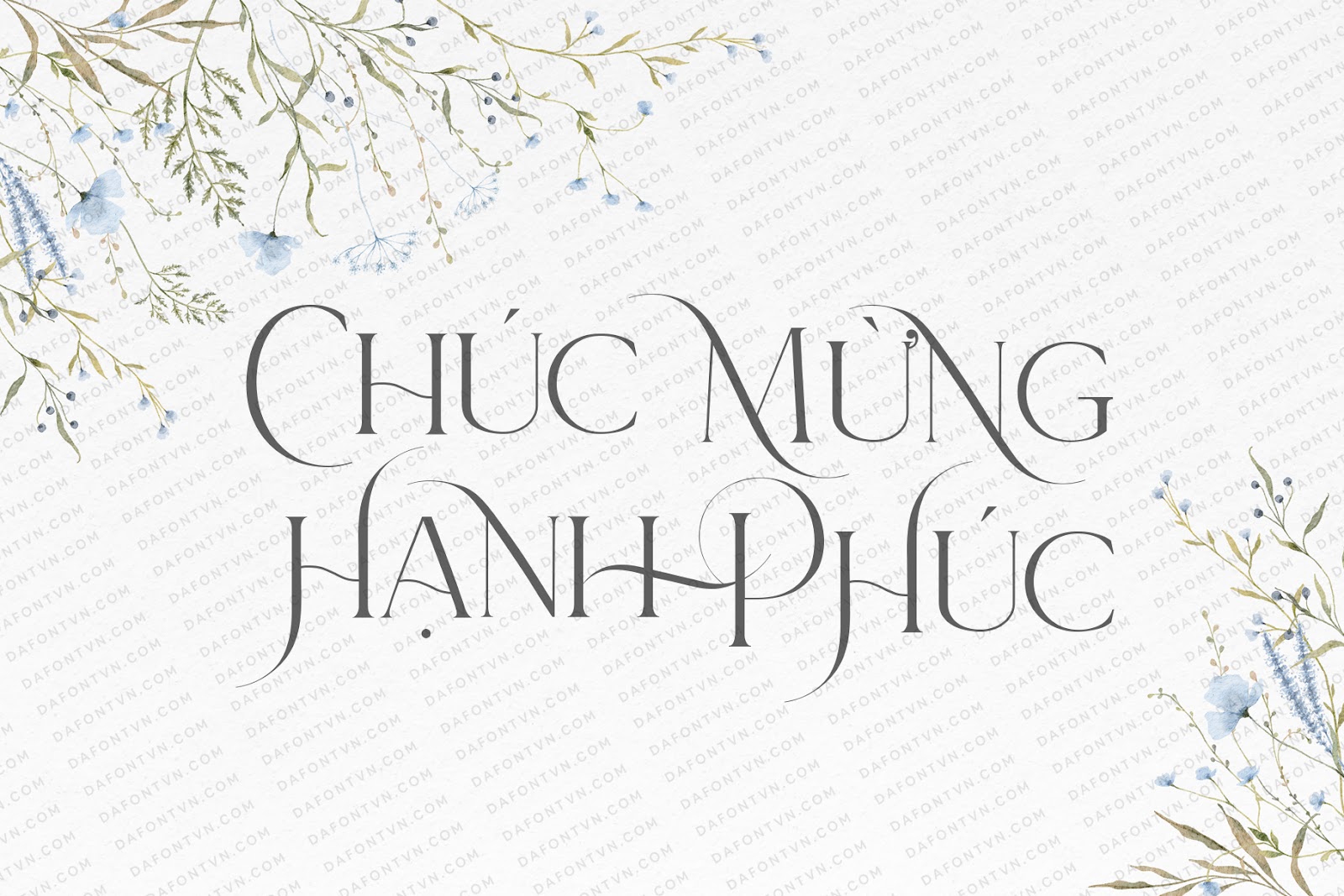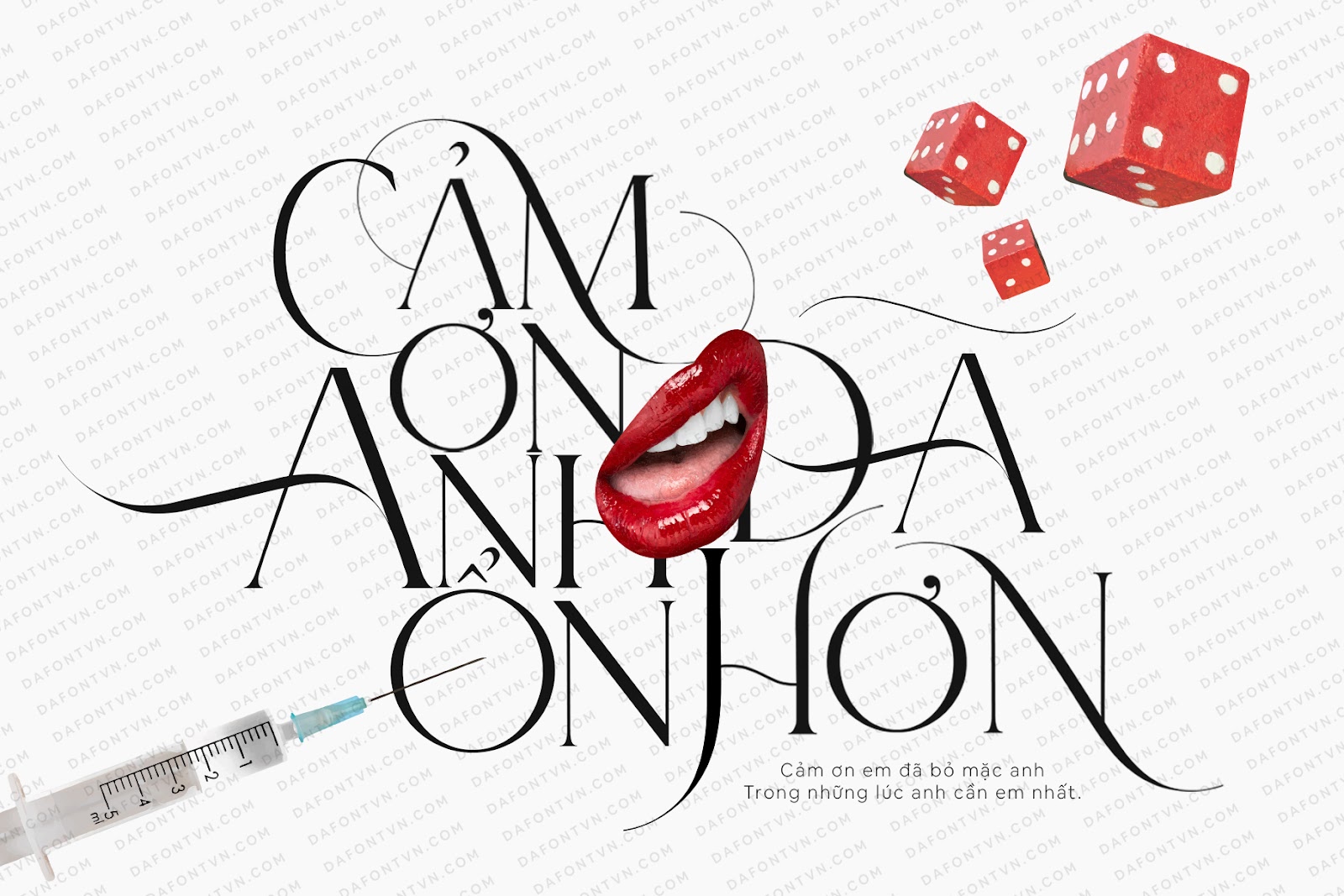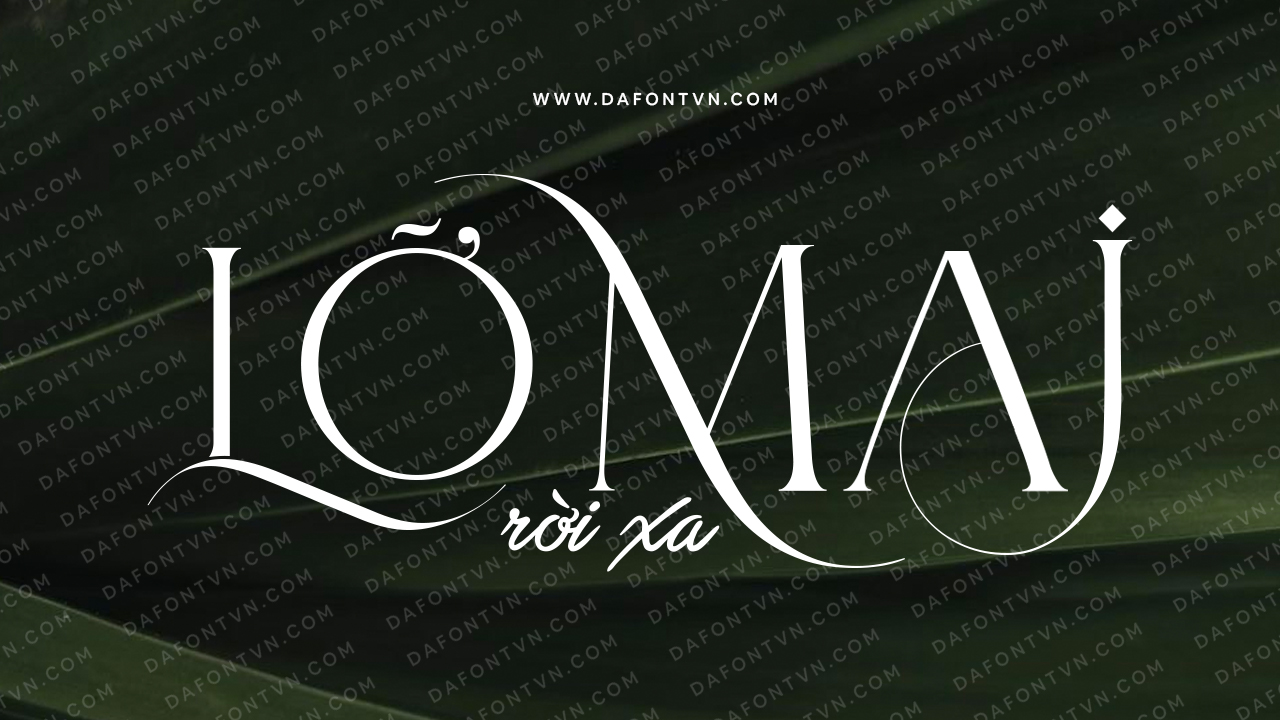
Le Major là font chữ serif thanh lịch, hiện đại sẽ mang đến cho dự án thiết kế của bạn nét sang trọng và phong cách.
Le Major là sự kết hợp hoàn hảo cho các thiết kế như đám cưới, thiệp mời, tiêu đề, logo, tạp chí… Với tất cả các nét chữ được viết hoa, tuy nhiên các nét chữ in hoa được thiết kế uốn lượn đẹp mắt. Ngoài ra bao gồm rất nhiều các ký tự thay thế đẹp mắt khác bạn có thể sử dụng nó trong bảng glyph để kết hợp tạo ra các thiết kế ấn tượng hơn nhé.